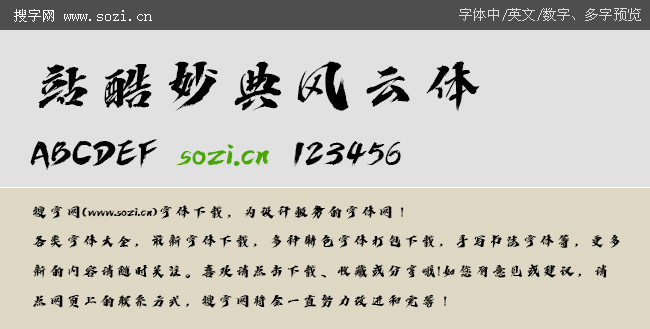
站酷妙典風云體
搜字網給大家提供一款站酷妙典風云體中文書法字體下載,站酷妙典風云體是一款風格硬朗且具有張力的手寫類毛筆字體,此款字體筆畫特點運用在撇捺勾轉折之間,適當的枯墨飛白、粗細對比的筆畫和帶有力量感的運筆方式,使字形在視覺上有更好的沖擊力,在活動海報、影視綜藝類等大標題字的設計上將會有更好的視覺效果。(本字體為個人非商用版,如需要商用請聯系作者購買版權)